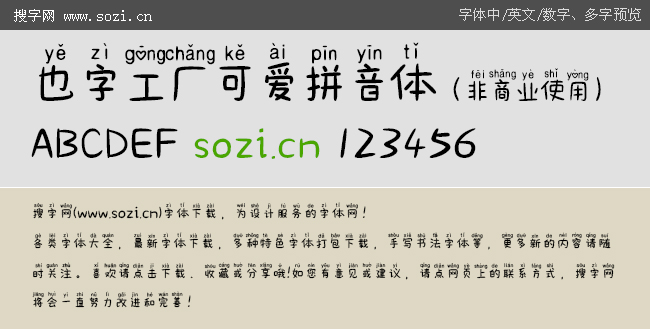
也字工廠可愛拼音體
搜字網(wǎng)給大家提供一款也字工廠可愛拼音體(非商業(yè)使用)中文字體下載,也字工廠可愛拼音體是一款卡通字體,字體是可愛的書寫風(fēng)格,非常可愛有趣,字體還搭配了漢語拼音。具有很好的視覺效果。適合應(yīng)用于兒童繪本、兒童海報(bào)、網(wǎng)頁設(shè)計(jì)等應(yīng)用(此字體為個(gè)人非商用版,商用可以聯(lián)系:官方網(wǎng)址:https://yefont.com/home,聯(lián)系方式:13798980448)。